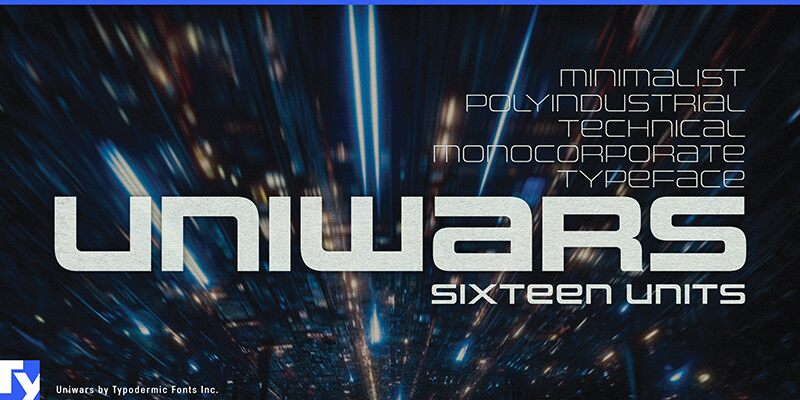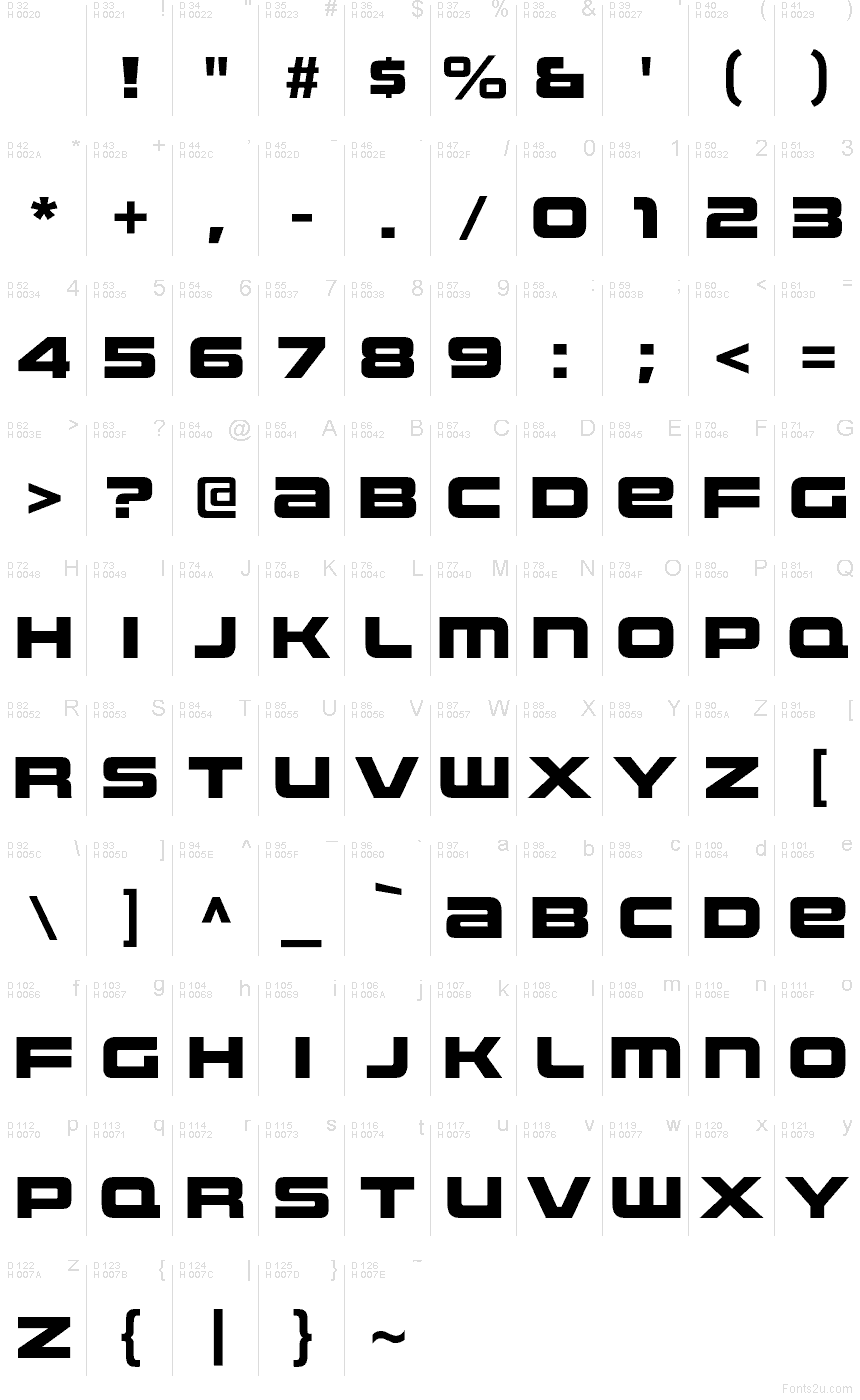
Uniwars Heavy von Typodermic Fonts Inc. ist eine kostenlose, futuristische Display-Schrift mit einem kompakten, monolithischen Rhythmus. Die Buchstaben wirken wie aus einem massiven Block gemeißelt – mit breiten, abgerundeten Ecken, kantigen Innenschnitten und fließenden horizontalen Verbindungen, die dem Alphabet eine schnittige Sci-Fi-Optik verleihen, wie man sie aus der Ära der frühen Videokonsolen kennt.
Damit ist diese Schrift die ideale Wahl für Gaming-Logos, Tech-Event-Plakate, E-Sport-Branding, Musik-Cover und Titelbilder, bei denen kurze Wörter einen wuchtigen, maschinellen Charakter benötigen. Sie eignet sich zudem hervorragend für interface-orientiertes Packaging oder Monogramme, da die kräftigen Formen und präzisen Kurven selbst bei wenigen Zeichen für ein bewusstes, konstruiertes Design sorgen.